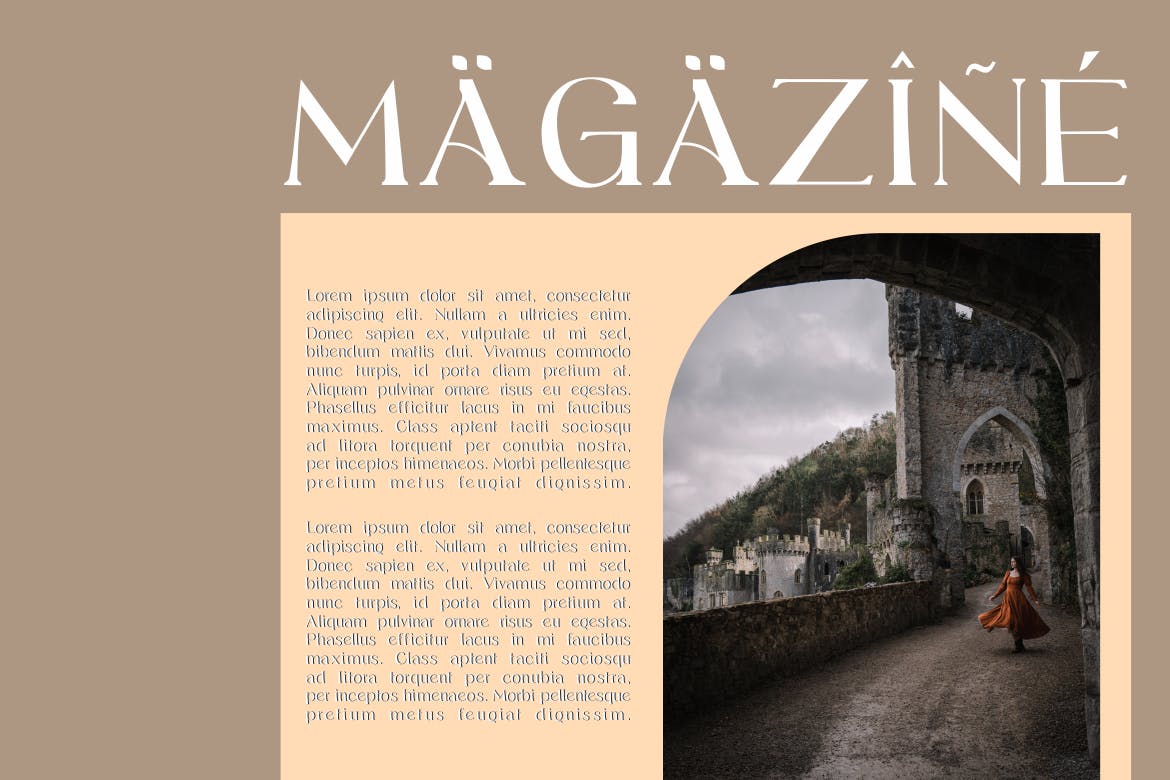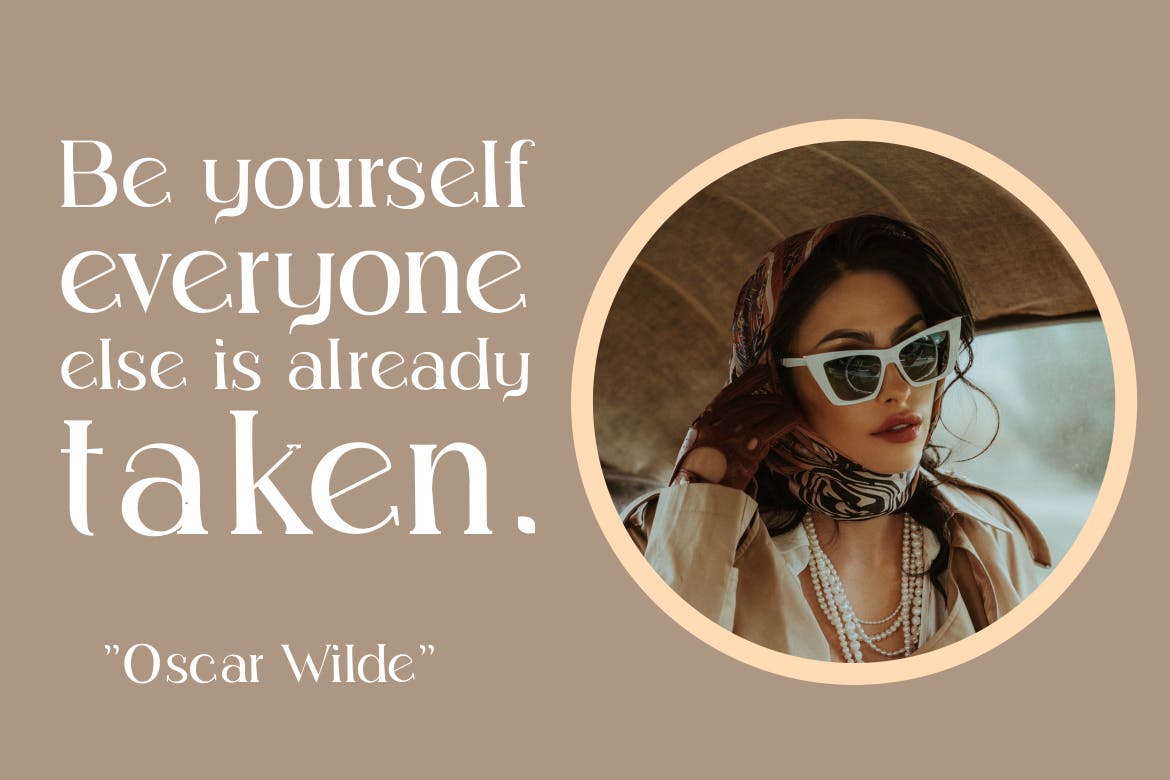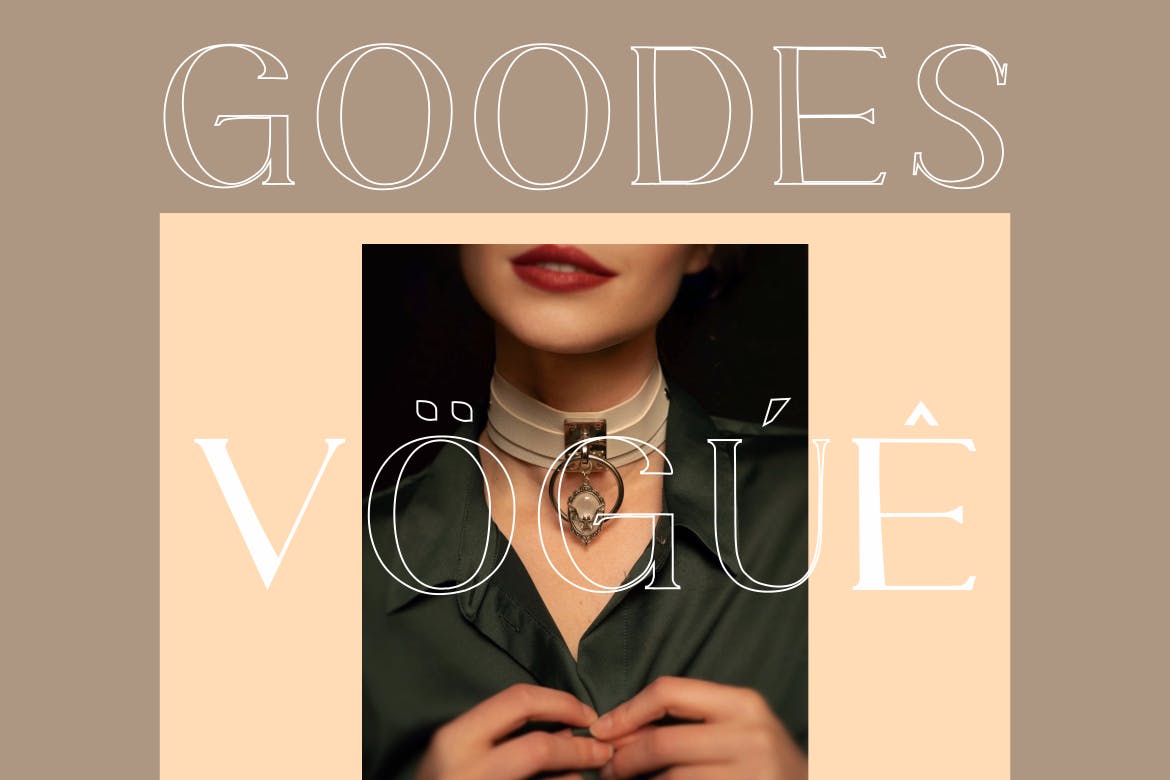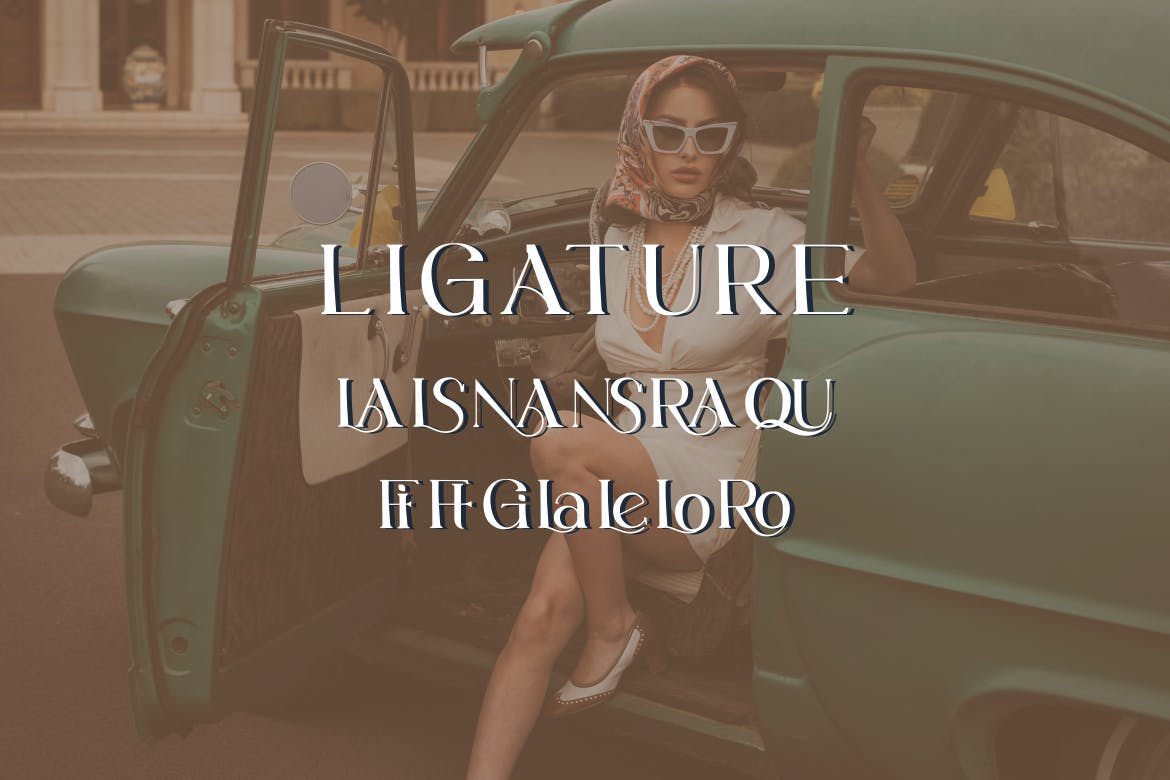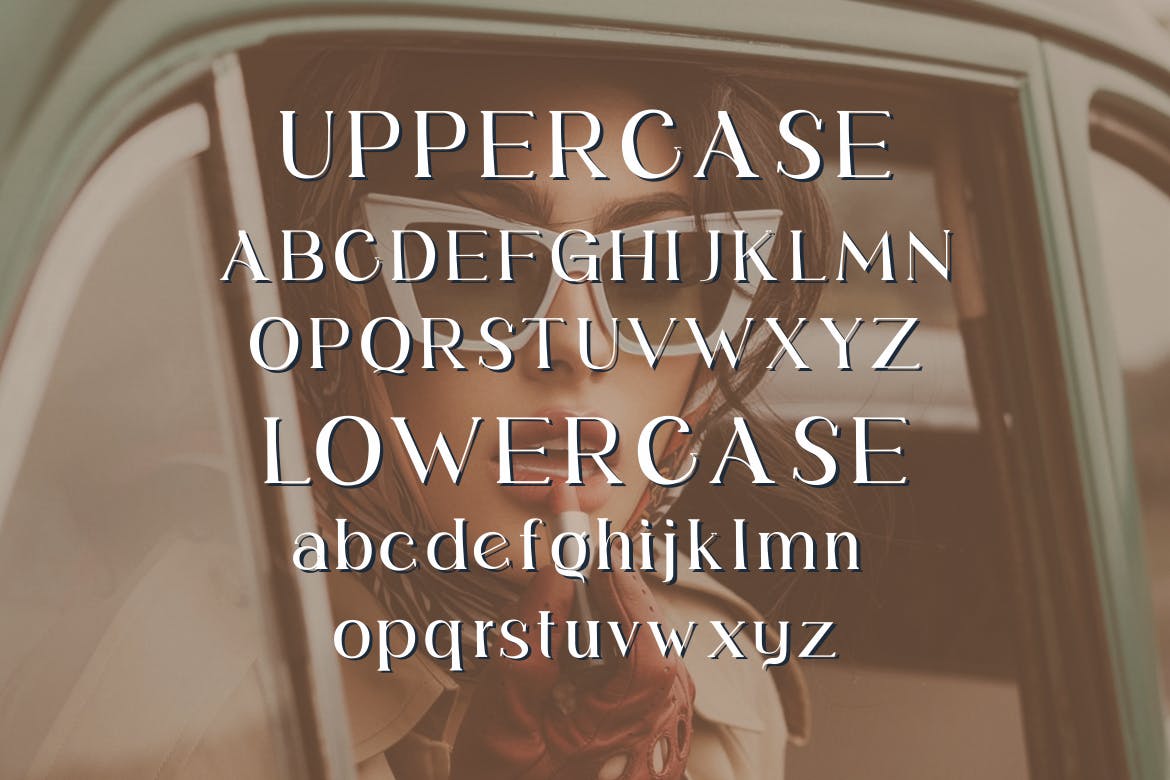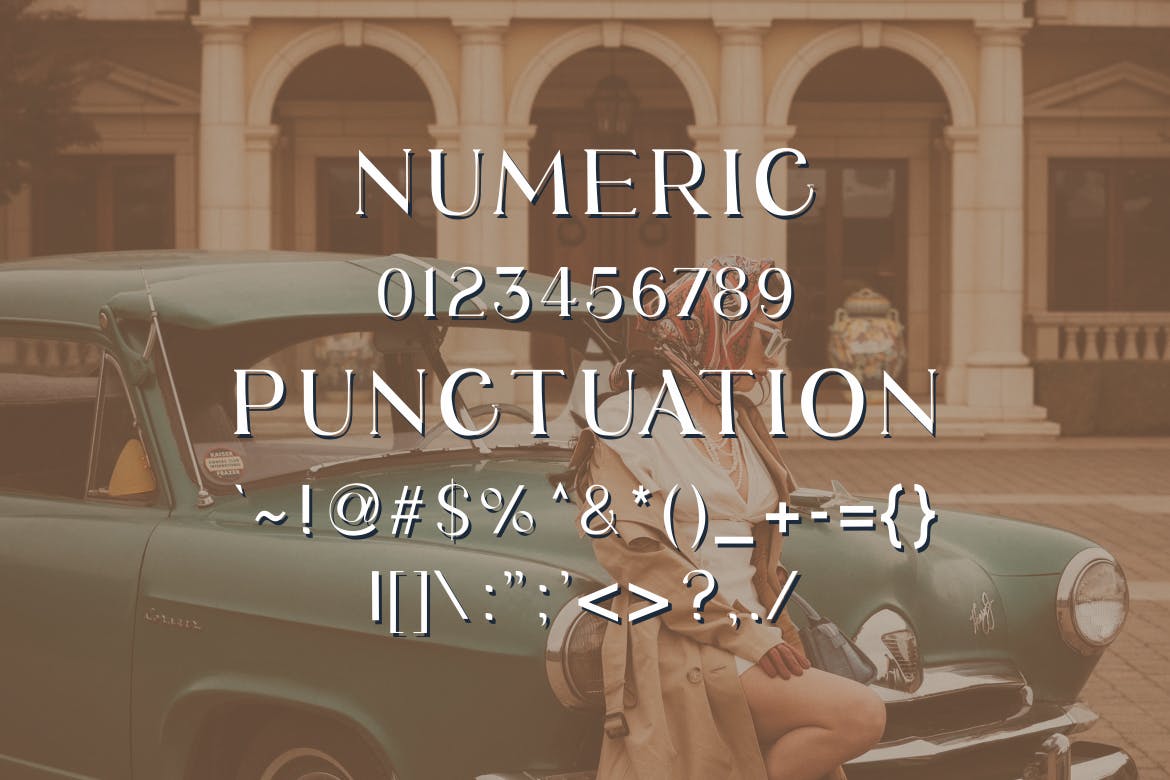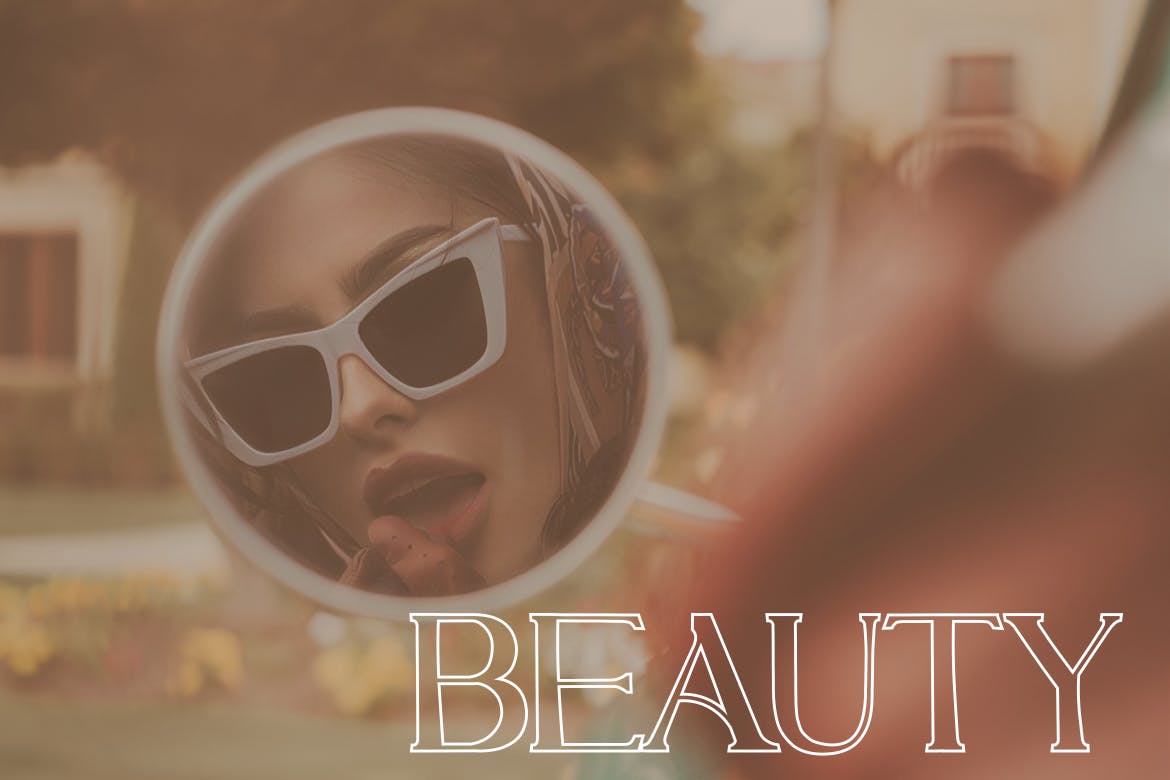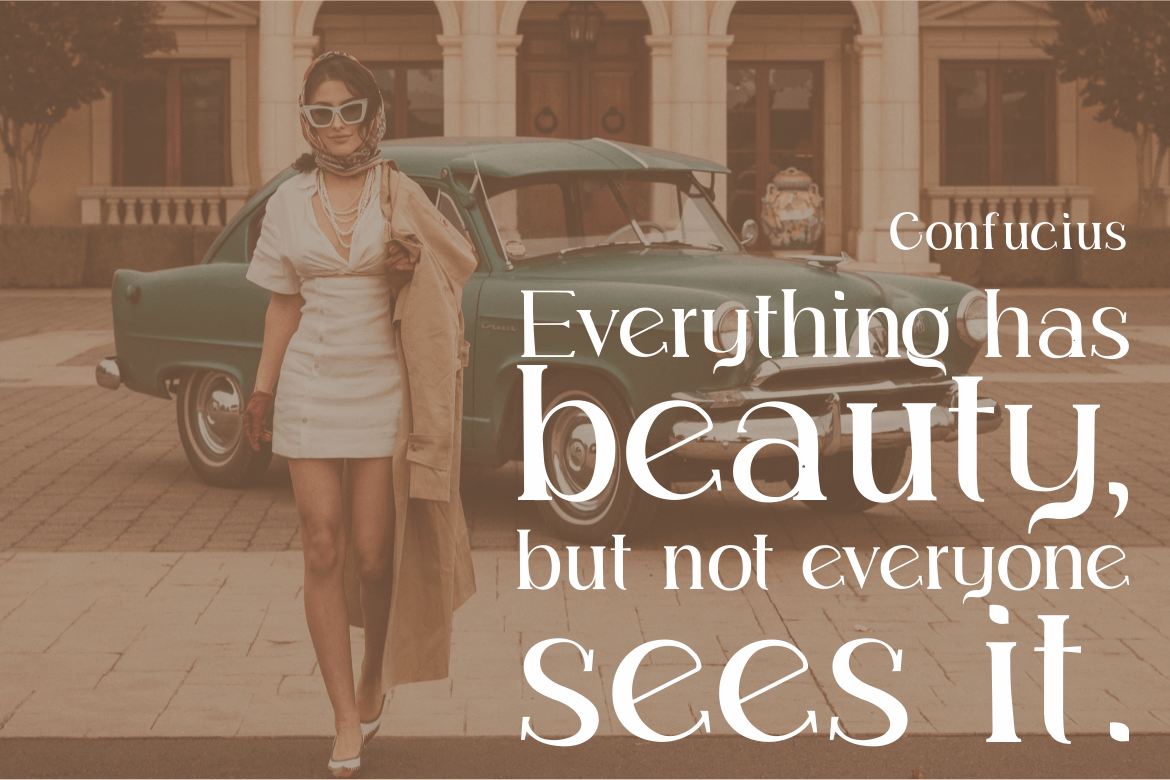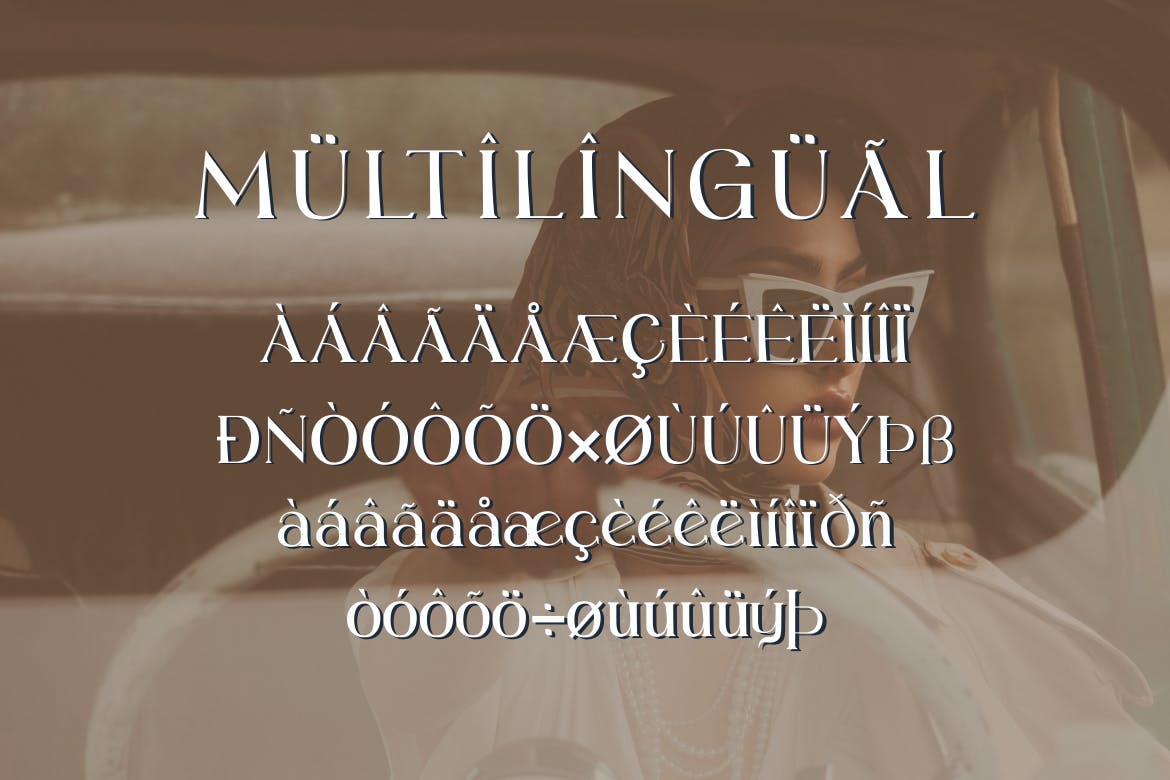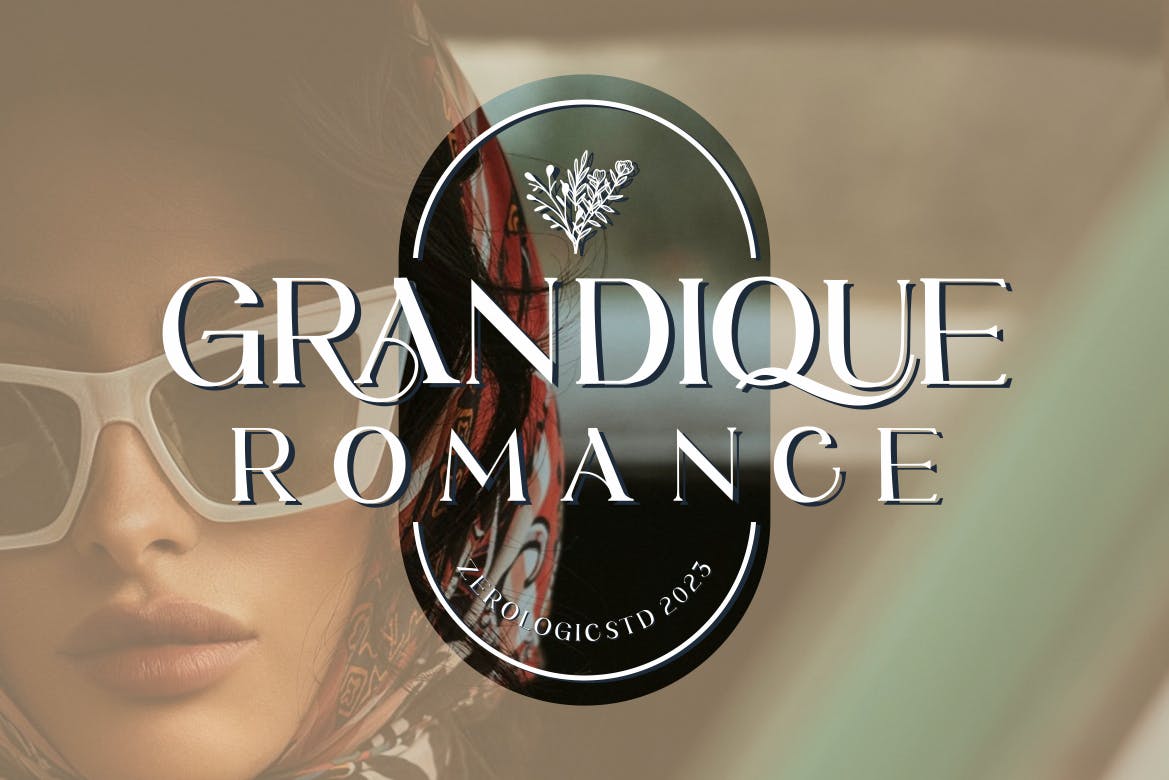
فونت Grandique Romance یک فونت مدرن و لوکس است که با لمس اصیل خود برای نیازهای شما طراحی شده است. این فونت جذاب شامل حروف بزرگ، حروف کوچک، اعداد و نمادها میباشد. این فونت قوی و تیز برای عناوین، تایپوگرافی، پوسترها، مجلات، بروشورها، بستهبندی، وبسایتها و بسیاری دیگر از پروژههای طراحی شما مناسب است و طراحیهای شما را جذابتر میکند.